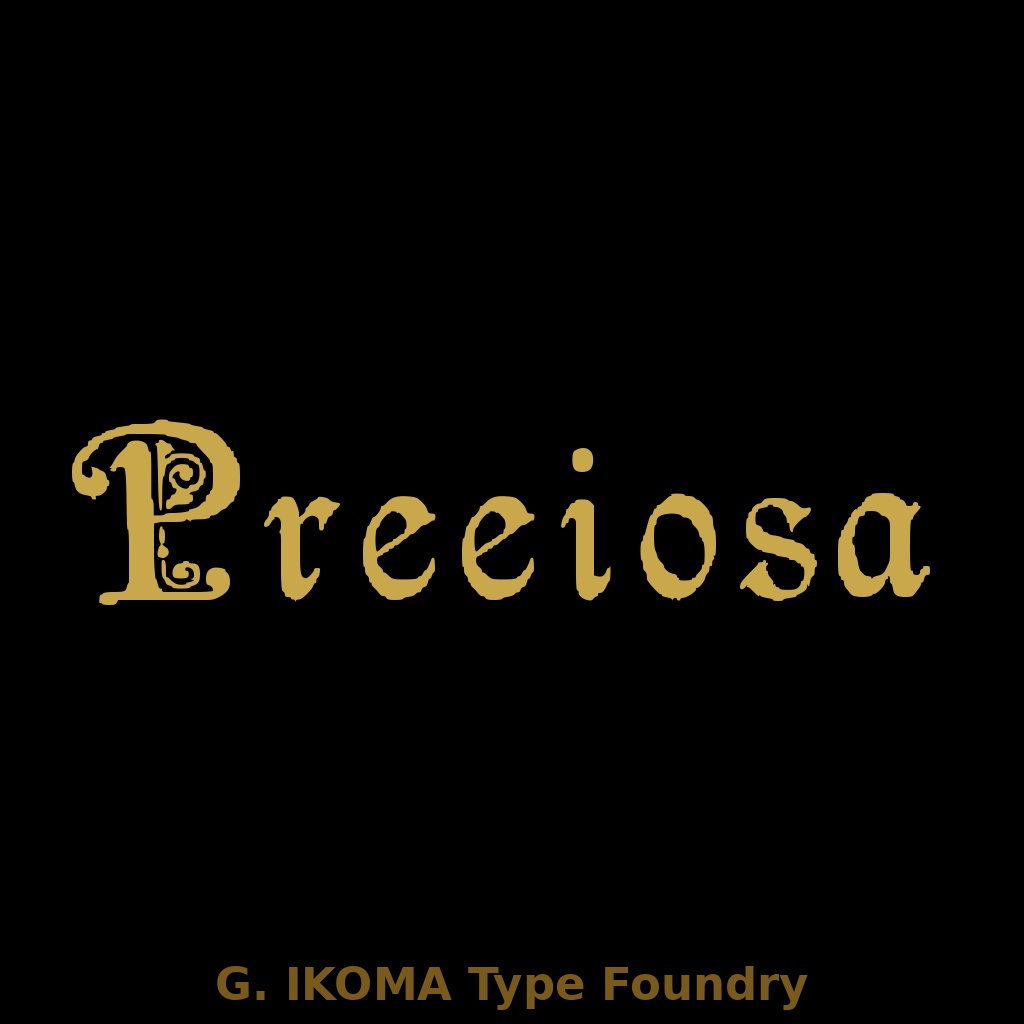
PREEIOSA — 19世紀欧州印刷資料復元フォント / Historical Revival Typeface [Ornamental Gothic]
━━━━━━━━━━━━━━━━━━━━━━━━━ 【フォントについて】 ━━━━━━━━━━━━━━━━━━━━━━━━━ PREEIOSA は、19世紀末〜20世紀初頭の欧州印刷資料を原典に、手作業でトレース・デジタル化した復元フォントです。 本作は、シュトゥットガルトの活字鋳造所 Schriftgiesserei Bauer & Co. による装飾 Gothic 書体をもとに再構成したものです。原典資料下部には 「Schriftgiesserei Bauer & Co., Stuttgart.」 と記されています。 唐草や渦巻きをあしらった装飾的大文字と、端正な Blackletter 系小文字の組み合わせが特徴で、重厚さと装飾性を併せ持つ書体です。 原典:Ludwig Petzendorfer, Schriften-Atlas 1898 (Neue Folge 1903) Julius Hoffmann, Stuttgart(パブリックドメイン) 様式:Ornamental Gothic / Blackletter 収録文字:大文字 A–Z、小文字 a–z、記号類 欠落文字:数字 0–9(原典に収録なし) 制作:株式会社生駒時計店 / G. IKOMA, LTD.(1870年創業) ━━━━━━━━━━━━━━━━━━━━━━━━━ 【ご購入前にご確認ください】 ━━━━━━━━━━━━━━━━━━━━━━━━━ 原典資料に数字(0–9)の収録がないため、本フォントにも数字は含まれていません。 そのため、数字を含む用途には適していません。 見出し、タイトル、ロゴ、エンブレムなど、装飾性を活かすディスプレイ用途 に向いています。 本文組版や、小サイズでの長文利用には向きません。 ━━━━━━━━━━━━━━━━━━━━━━━━━ 【収録内容】 ━━━━━━━━━━━━━━━━━━━━━━━━━ ・PREEIOSA.ttf ・LICENSE.txt ・specimen.pdf(収録文字見本・使用イメージ) ━━━━━━━━━━━━━━━━━━━━━━━━━ 【推奨用途】 ━━━━━━━━━━━━━━━━━━━━━━━━━ ・ロゴ ・見出し ・書籍タイトル ・ゲームタイトル ・紋章 ・エンブレムデザイン ・装丁 ・ラベル ・バナー画像 ・サムネイル画像 Gothic 系の重厚な装飾を必要とするディスプレイ用途 に適しています。 本文組版や小サイズでの常用には向きません。 ━━━━━━━━━━━━━━━━━━━━━━━━━ 【ライセンス】 ━━━━━━━━━━━━━━━━━━━━━━━━━ 本フォントは、個人利用・商用利用を問わず、印刷物、画像、ロゴ、バナー、動画サムネイル等の制作に使用できます。 また、WebサイトやSNSで画像化された状態で使用することは可能です。 ただし、以下の行為は禁止します。 ・フォントファイルそのものの再配布、再販売、譲渡、共有 ・改変したフォントファイルの配布 ・本フォントを素材集、テンプレート、デジタル商品等に収録して再販売する行為 ・本フォントファイルをWebフォントとしてサーバーに設置・配信して利用する行為 ・アプリケーション、ゲーム、ソフトウェア、電子機器等への埋め込み利用 ・AI学習、機械学習、生成モデル訓練等への利用 ・本フォント自体または収録字形そのものについて独占的権利を主張する行為 詳細は同梱の LICENSE.txt をご確認ください。 ━━━━━━━━━━━━━━━━━━━━━━━━━ 【原典資料について】 ━━━━━━━━━━━━━━━━━━━━━━━━━ 本フォントは、G. IKOMA, LTD. 所蔵の実物資料をもとに制作しています。 原典資料そのものは本商品に含まれていません。 資料アーカイブについては、下記サイトをご参照ください。 G. IKOMA Archive https://g-ikoma-archive.netlify.app/